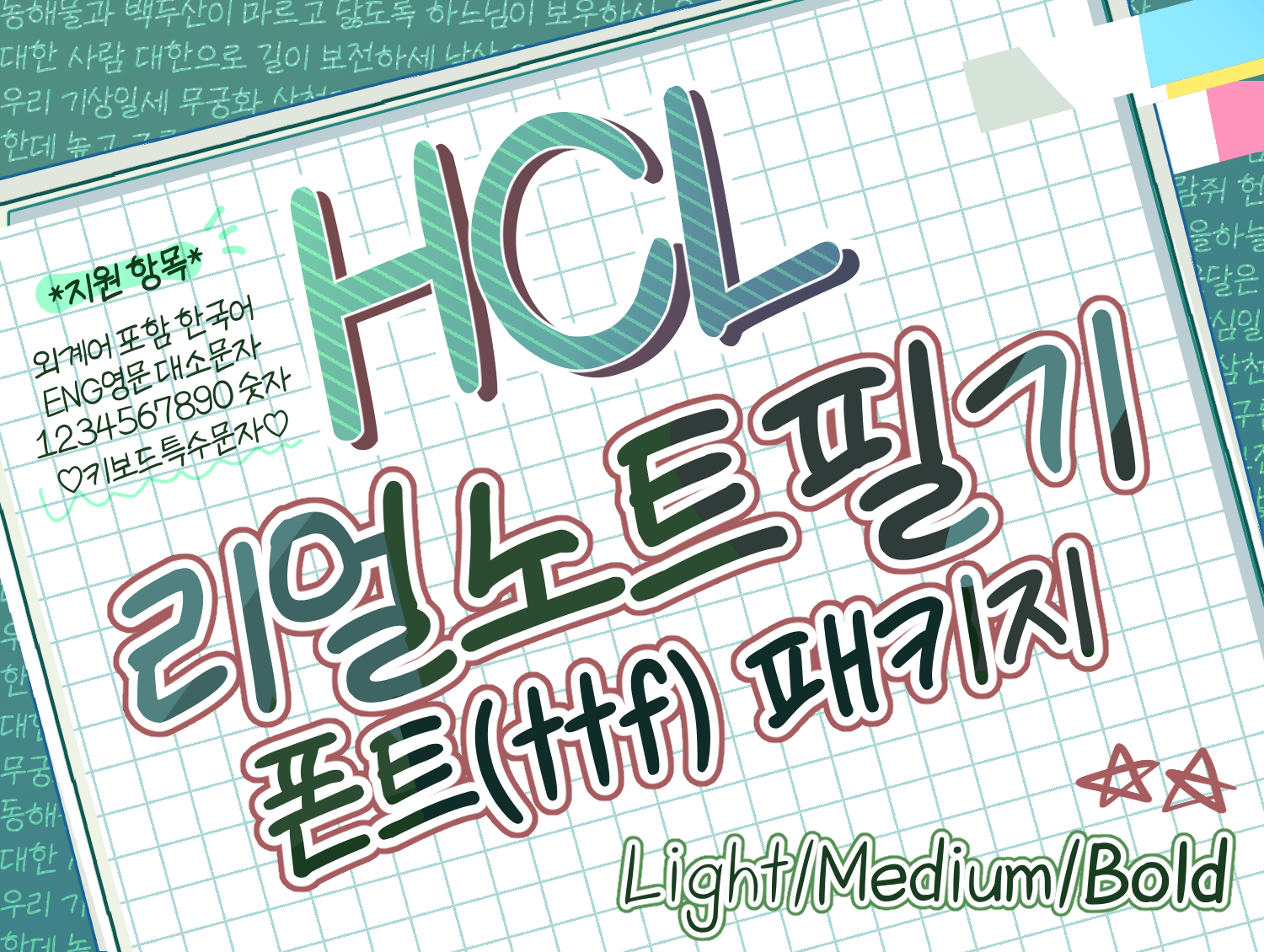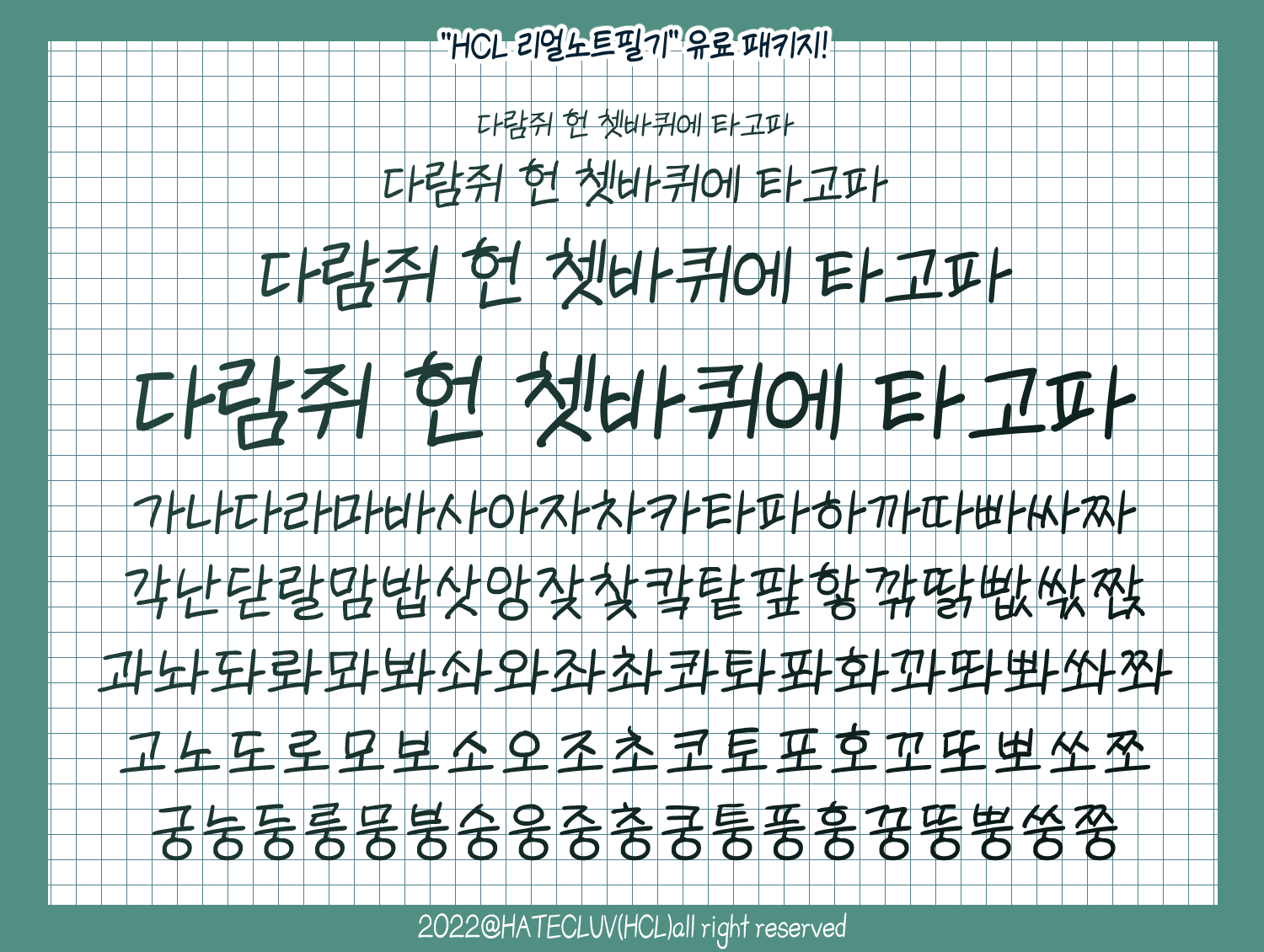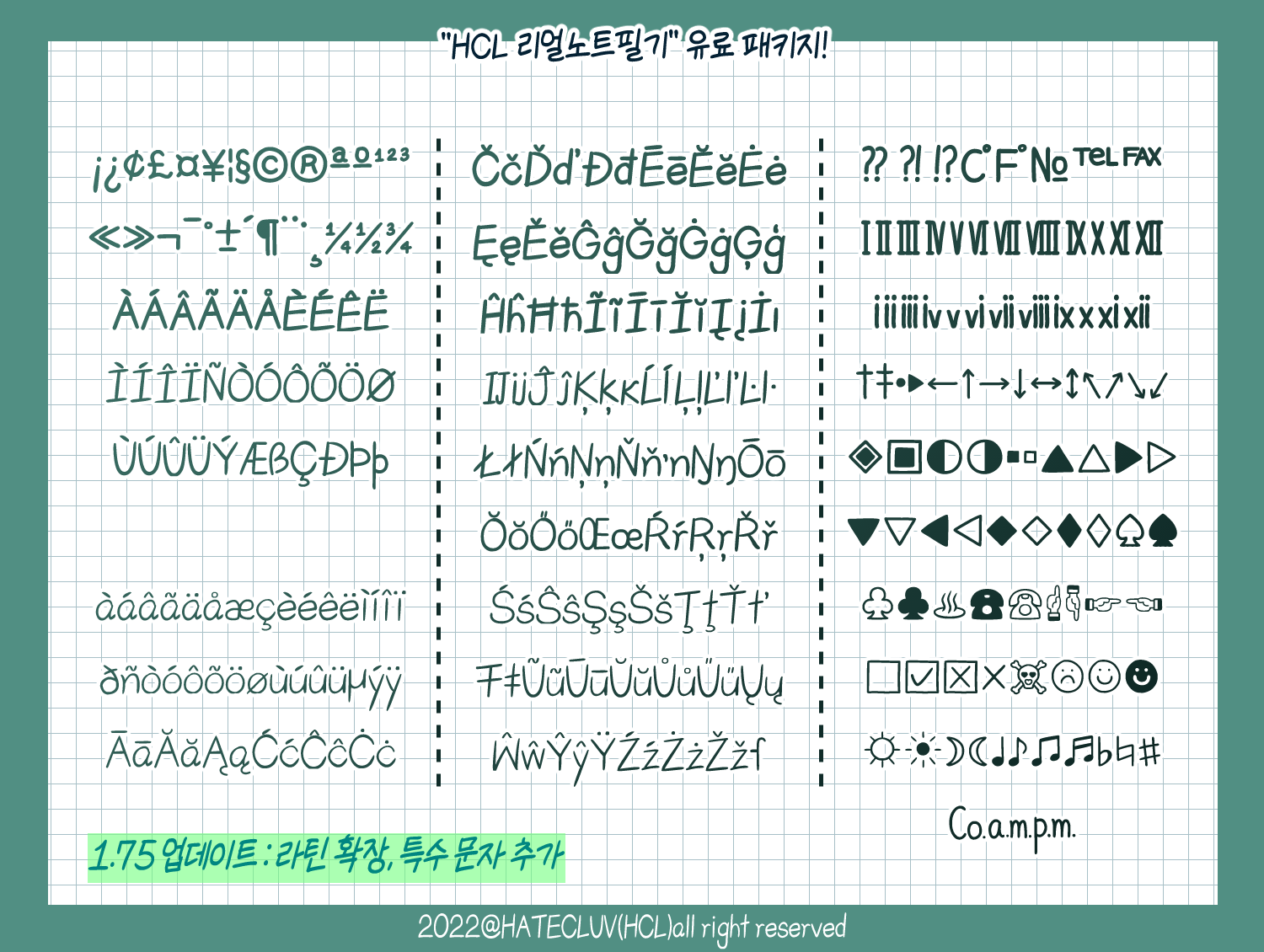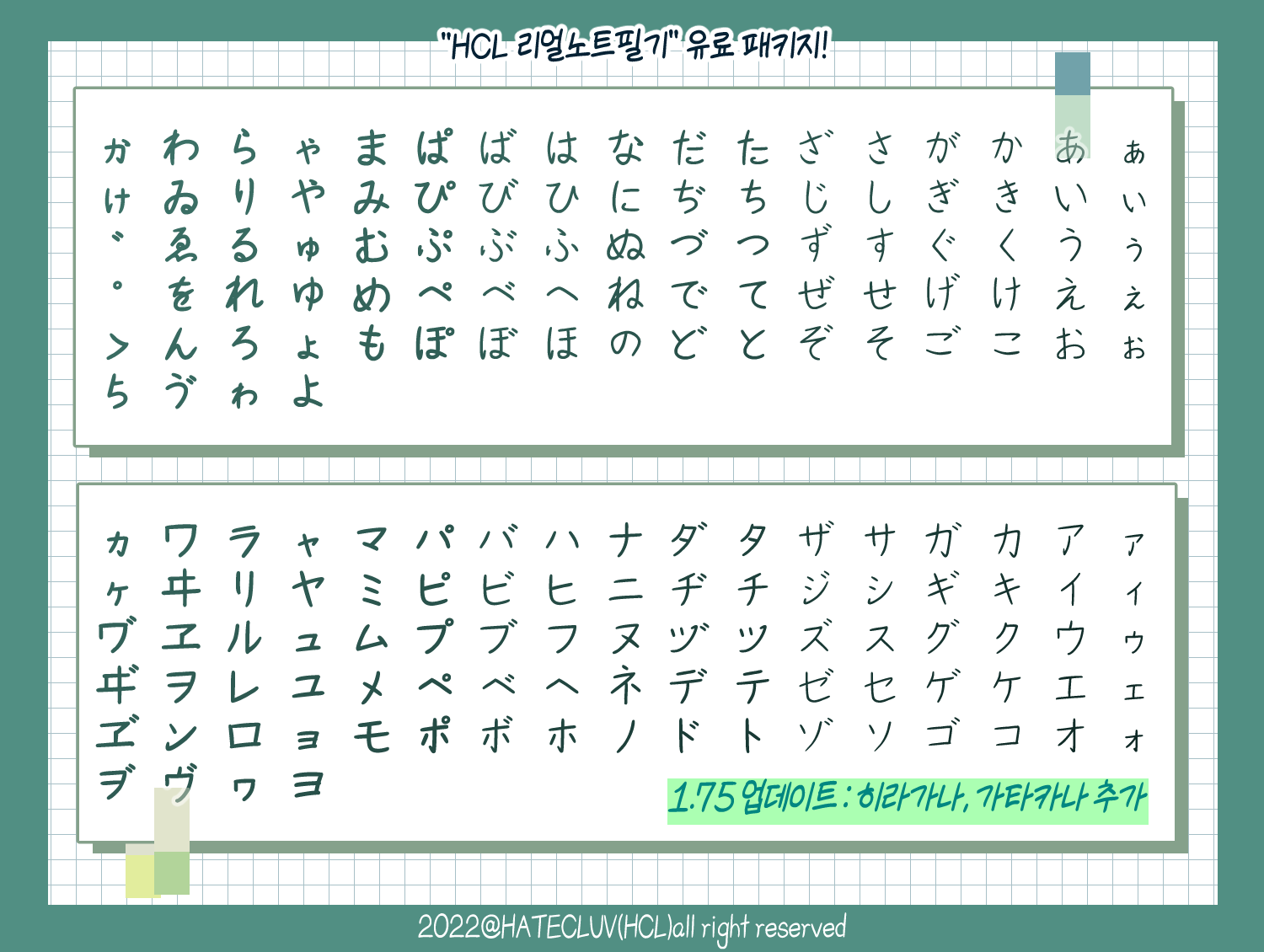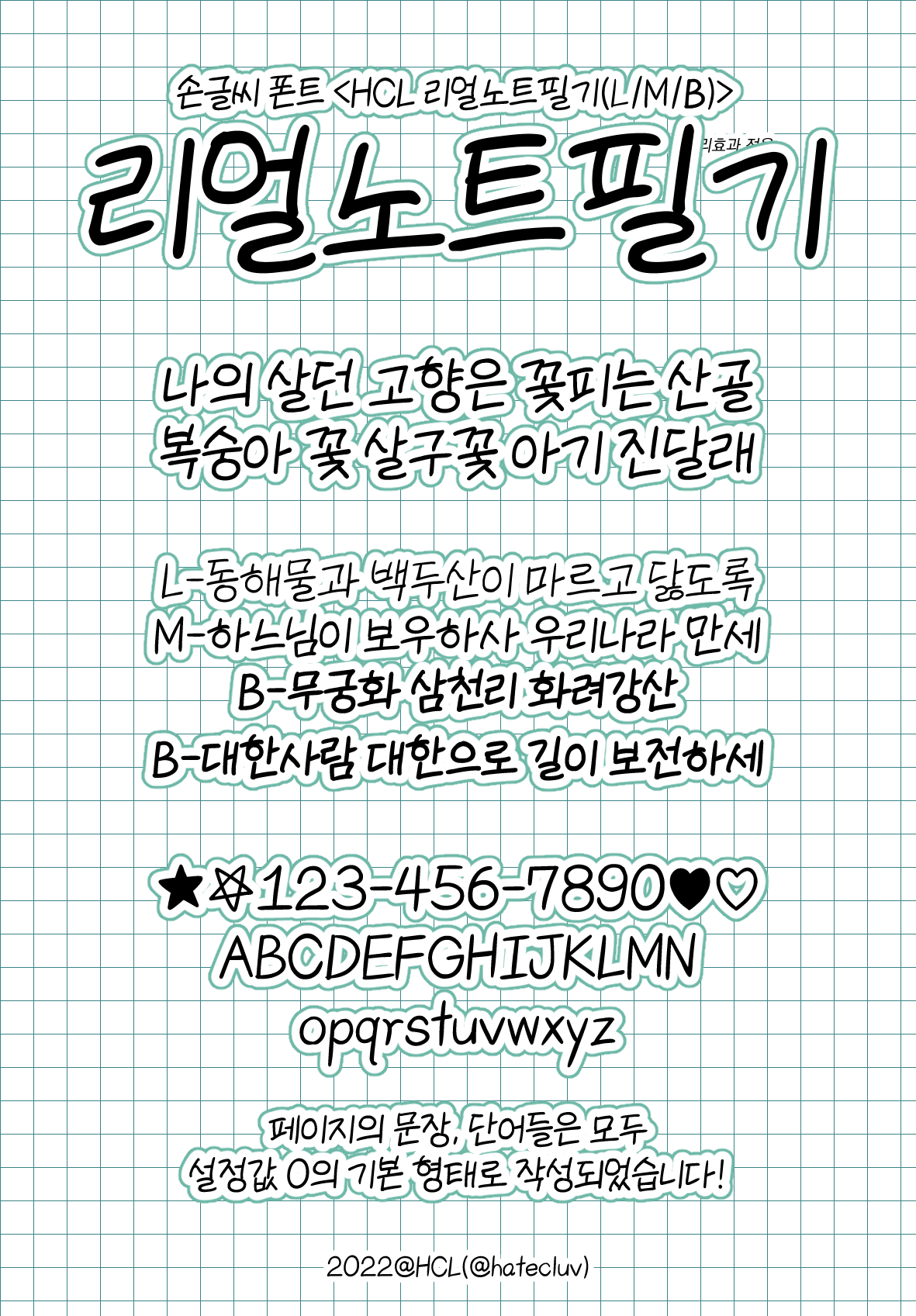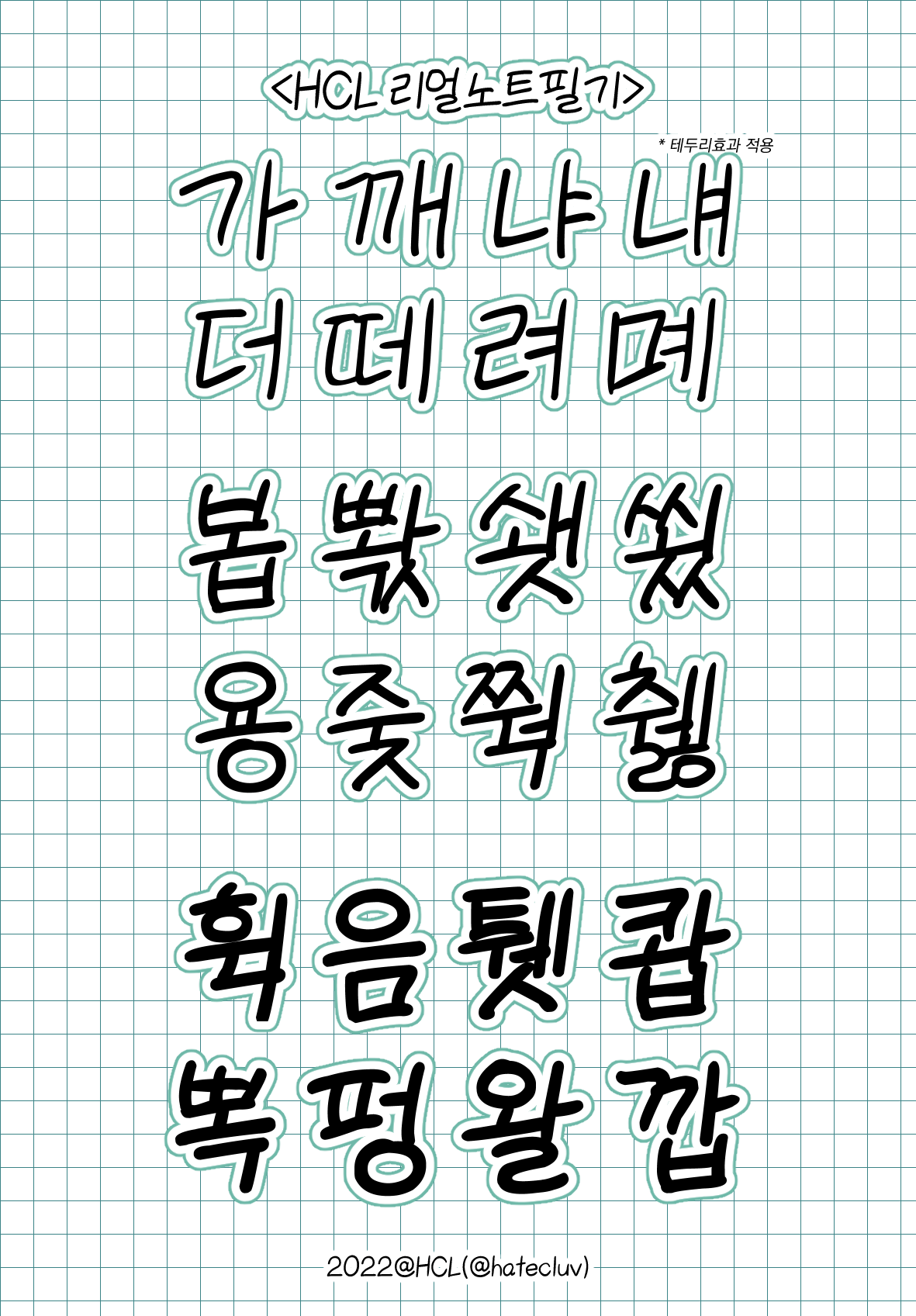
귀여운 느낌의 손글씨 폰트 <HCL 리얼노트필기> 입니다.
- 지원 항목
한글 조합 11172자 전체, 한글 기본 자모음 52자(ㄱ,ㄴ,ㄷ,ㅏ,ㅑ,ㅓ...)
한글 외 약 600자
1) 영문 대소문자(A,a...), 숫자(1,2,3...), 키보드 쉬프트 특수문자(!,@,#...)
2) 히라가나, 가타카나
3) 라틴 확장 문자(불어 및 일부 유럽어) 지원
4) 특수 기호(기본 도형, 하트, 별, 화살표, 로마 숫자, 음표, 전화기, 스마일, 해골 등)
HCL 리얼노트필기